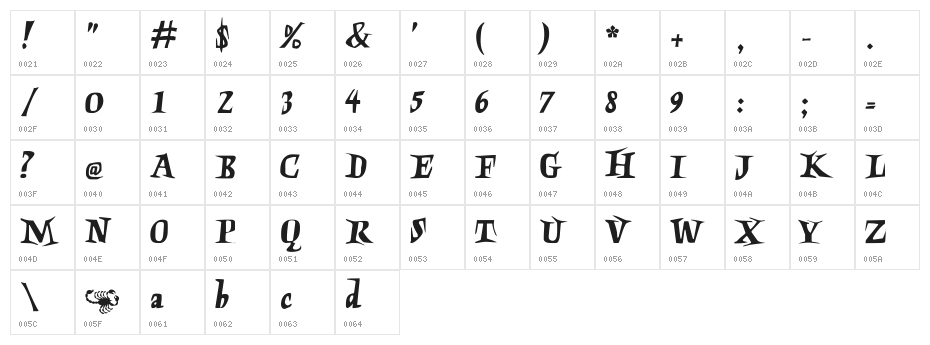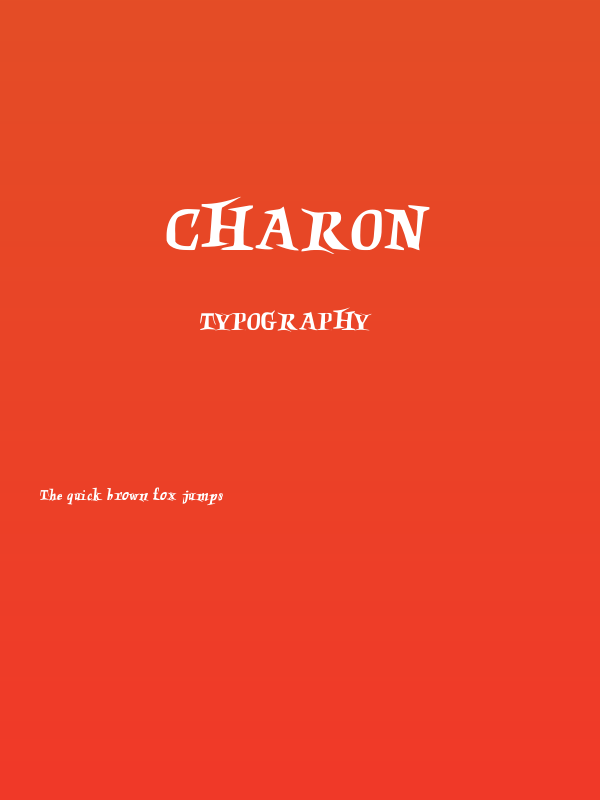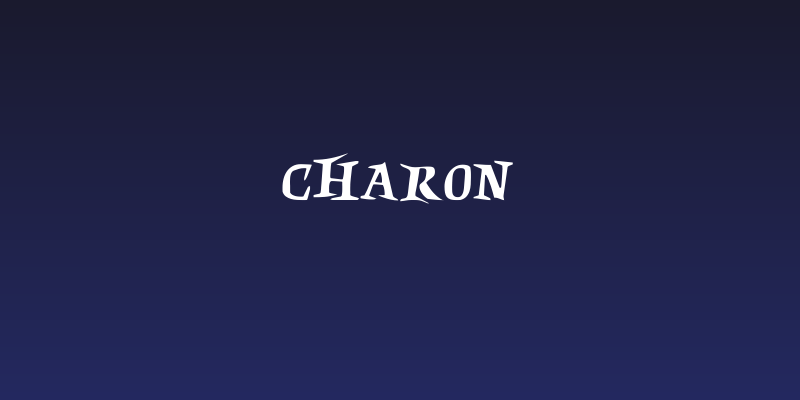
Charon Font
| Kategorien | Serif |
| Gesamtstil | Gothic, Decorative |
| Vorgeschlagene Projekte | Ideal for album covers, posters, branding for edgy or alternative products, and any design needing a bold statement. |